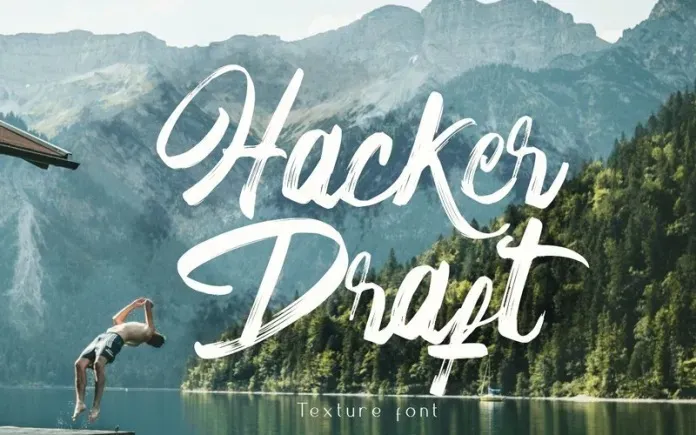
Essa fonte script é perfeita para quem busca uma paleta vibrante e natural, combinando traços aéreos com texturas seca e suaves. Ideal para logomarcas, adesivos de nome tag, citações escritas à mão, embalagens de produtos, mercadorias, materiais de mídia social e cartões de cumprimento. É perfeita para designers que buscam economizar tempo em criar designs de produtos, seja para roupas customizadas ou qualquer outro produto. O pacote inclui uma completa variedade de letras maiúsculas e minúsculas, um grande leque de pontuação e números, além de suporte multilíngue. Sua beleza artesanal torna-a uma escolha perfeita para quem deseja dar um toque único às criações digitais.